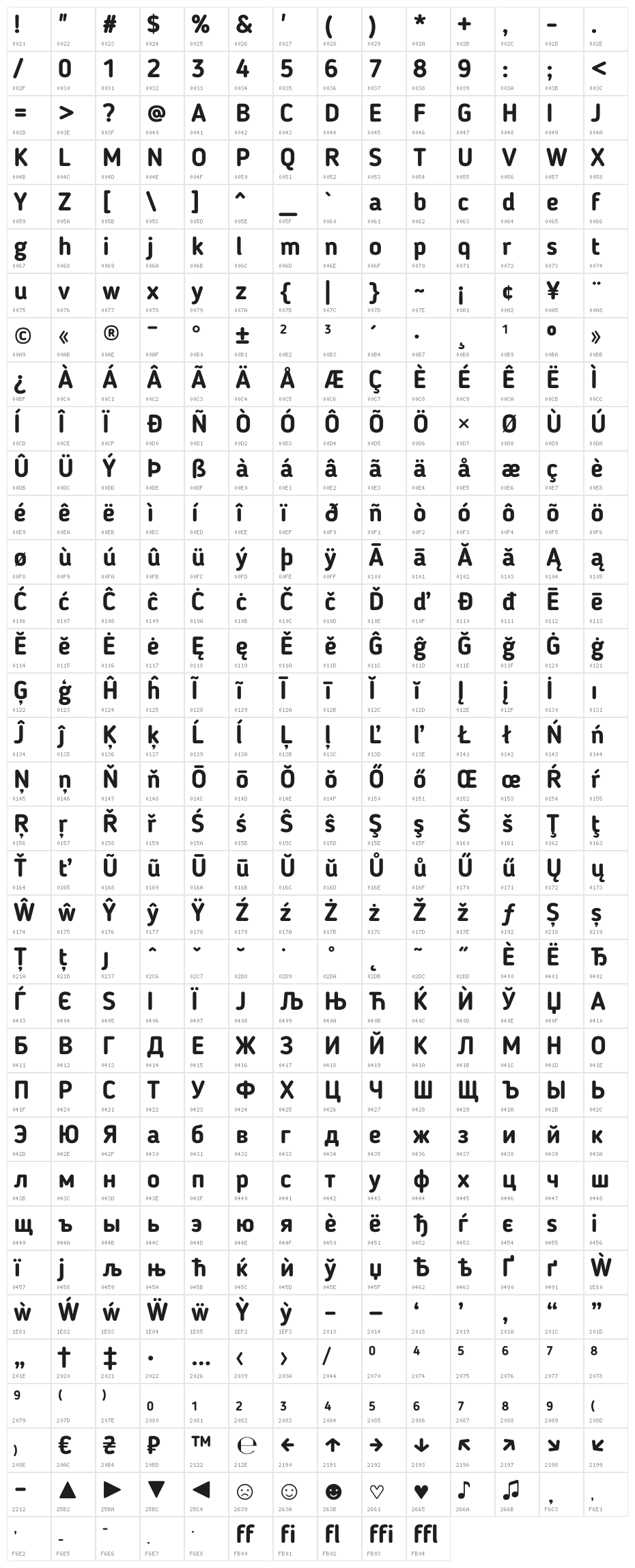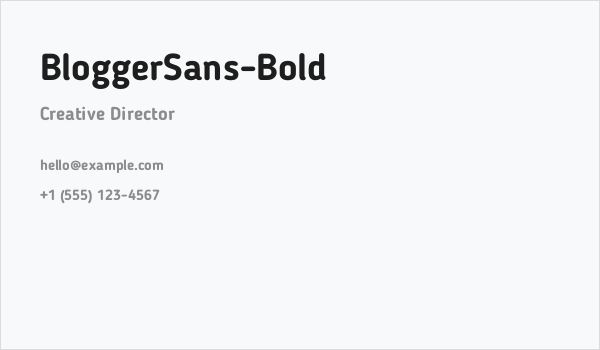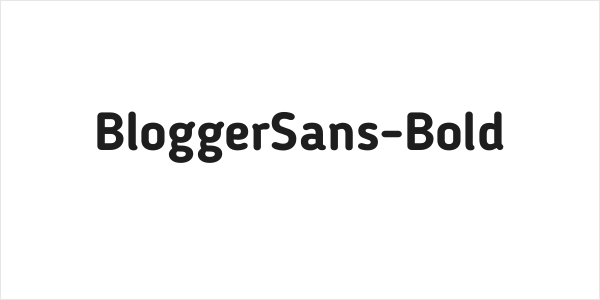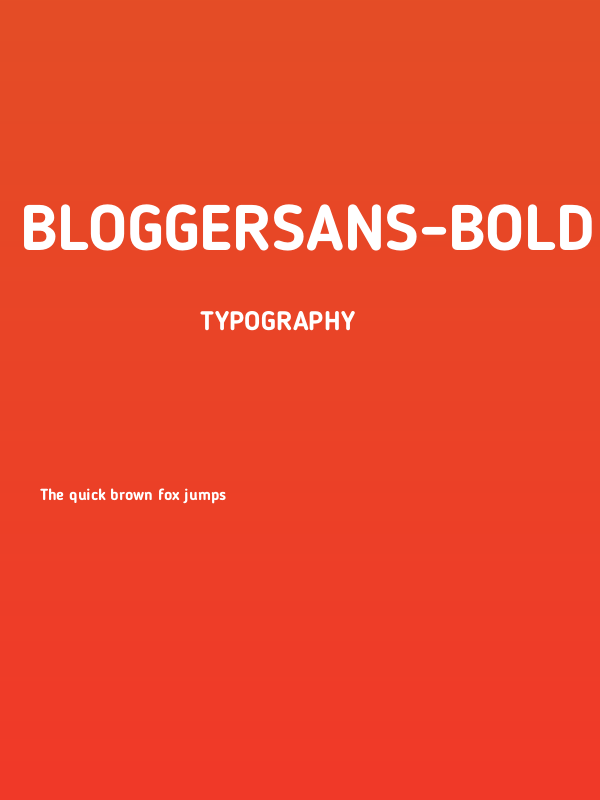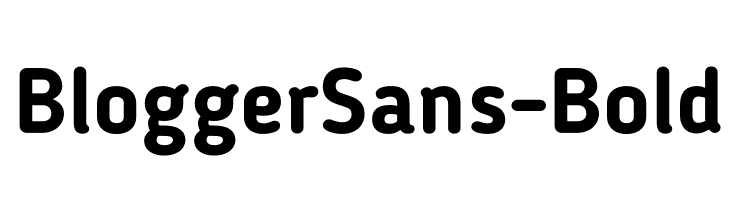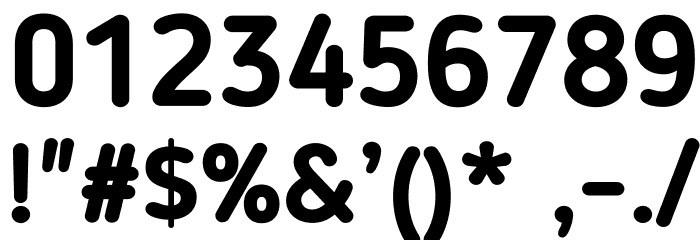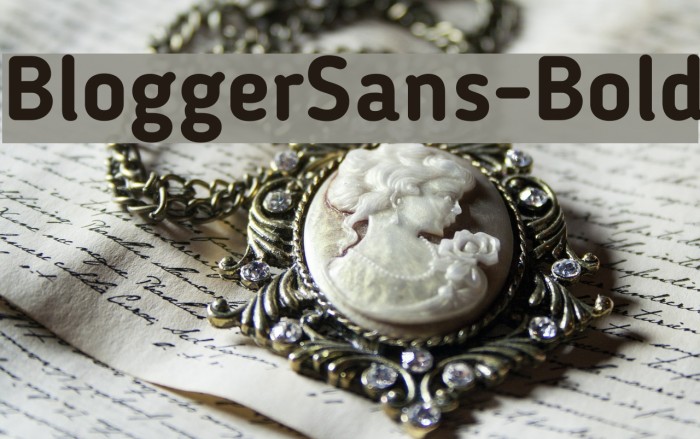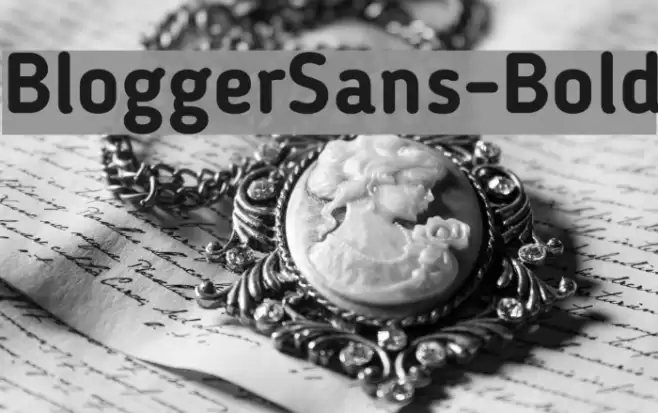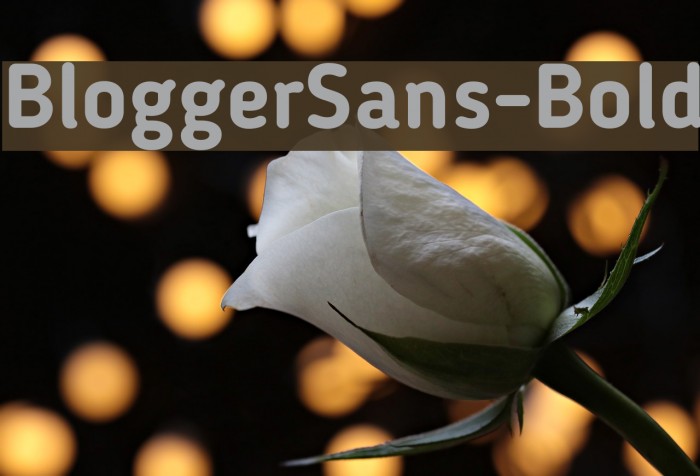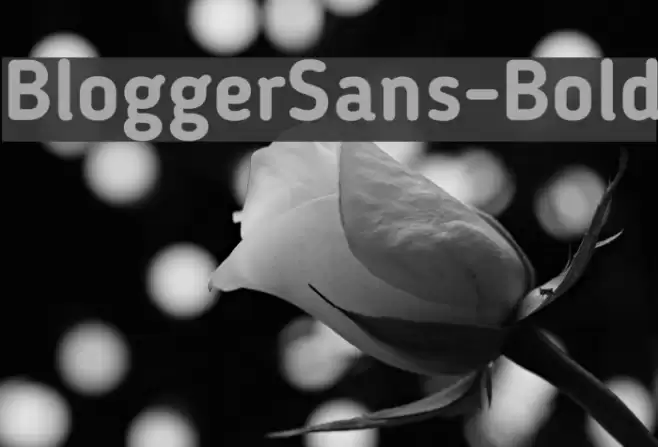
BloggerSans-Bold Font
BLOGGERSANS-BOLD 大文字
BLOGGERSANS-BOLD 小文字
BLOGGERSANS-BOLD その他の文字
| おすすめプロジェクト | Ideal for branding, advertising, web design, and user interfaces due to its readability and modern style. |